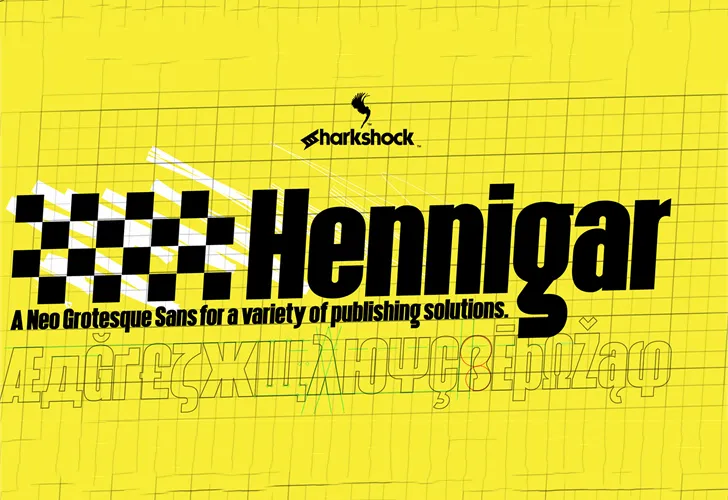
A Hennigar é uma elegante fonte em tipo aberto (OTF), ideal para estilos modernos e versáteis. Lançada pelo designer Sharkshock, essa fonte abrange tanto um estilo clean quanto um alternativo que adiciona interessantes contrastes ao seu design. A Hennigar oferece duas variedades: uma no formato regular e outra em itálico, proporcionando flexibilidade para uso em diversos projetos gráficos e tipográficos. Desenvolvida pelo designer Dennis Ludlow em 2016, essa fonte abrange um amplo leque de caracteres que se adaptam perfeitamente a uma ampla gama de aplicações, desde design editorial até logotipos criativos. Suas linhas curvadas e formas arredondadas complementam-se perfeitamente para criar visuais profissionais e contemporâneos. Na categoria de fontes sans serif, a Hennigar é uma escolha inteligente para quem busca um estilo minimalista que não compromete a legibilidade. Suas linhas retas, diretas e limpas oferecem um contraponto natural aos detalhes arredondados, resultando em um design atemporal que se destaca. Com o uso da Hennigar, você pode adicionar uma personalidade única a qualquer projeto visual, trazendo à tona elementos importantes e simplificando componentes secundários de forma consistente. Esta fonte é tanto útil quanto estilosa, tornando-a uma escolha perfeita para aqueles que desejam um toque moderno em seus trabalhos gráficos sem sacrificar a precisão ou a legibilidade.